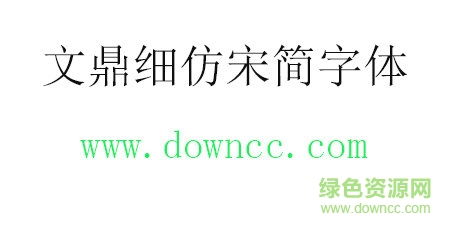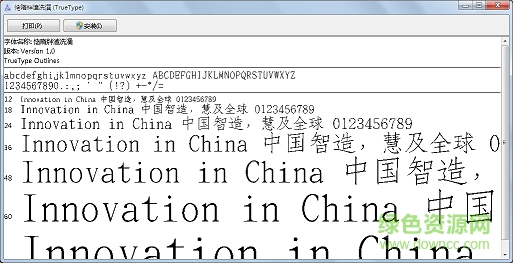
文鼎細(xì)仿宋簡(jiǎn)字體是一款筆畫(huà)細(xì)膩的中文簡(jiǎn)字體。該字體的給人的感覺(jué)像有點(diǎn)傾斜樣,有種飄逸感,適合寫(xiě)小說(shuō)或者大篇幅文章的朋友使用,能夠讓你的文章更加具有個(gè)性魅力,感興趣的朋友就快來(lái)綠色資源網(wǎng)下載使用吧!
文鼎細(xì)仿宋簡(jiǎn)字體的主要特點(diǎn)是方正雅觀,結(jié)構(gòu)條理清晰,字符覆蓋面廣,覆蓋了絕大部分的漢字,包括一些生僻字,且小字體清晰,小而不失字體特點(diǎn),是設(shè)計(jì)中被廣泛使用的字體。